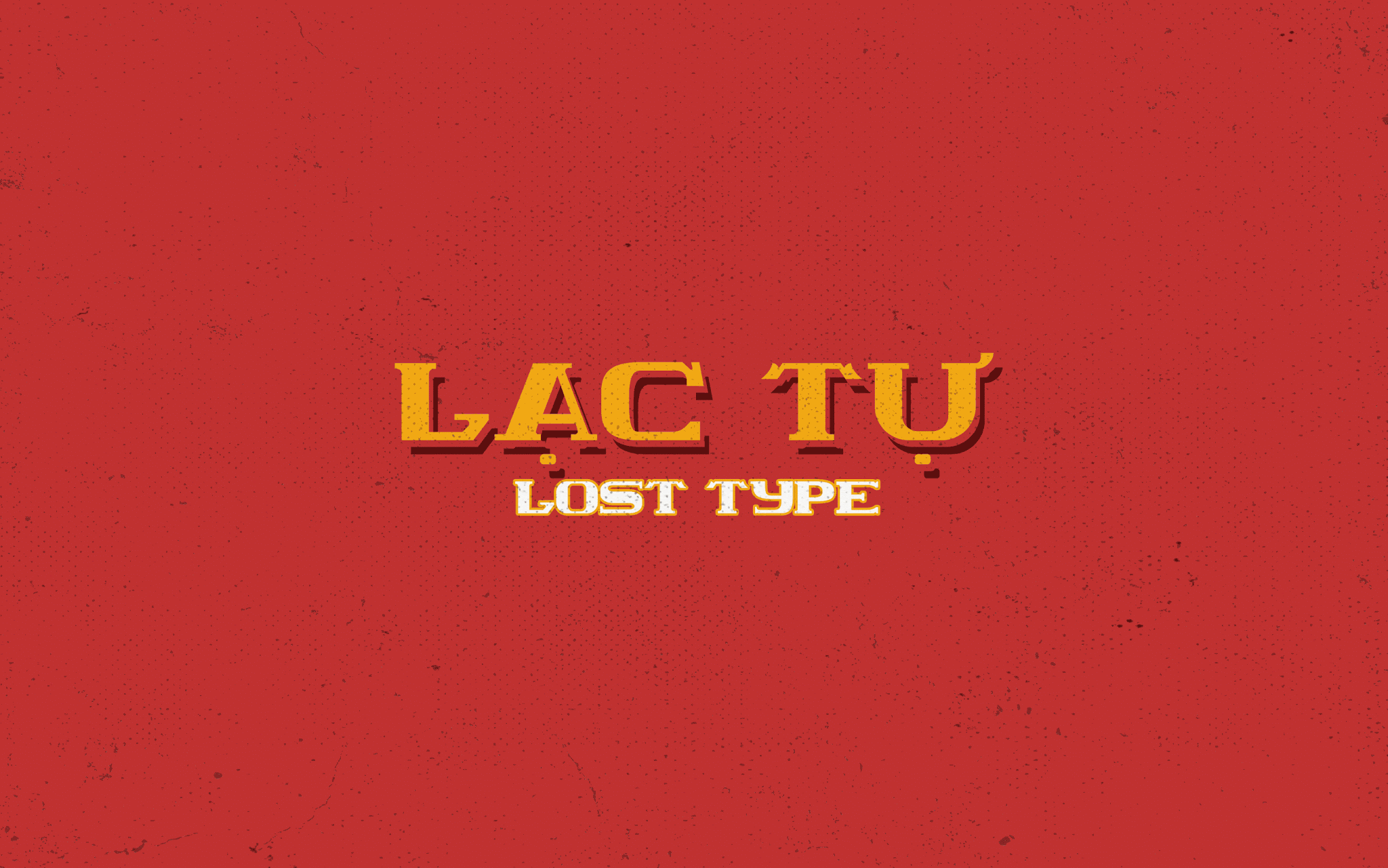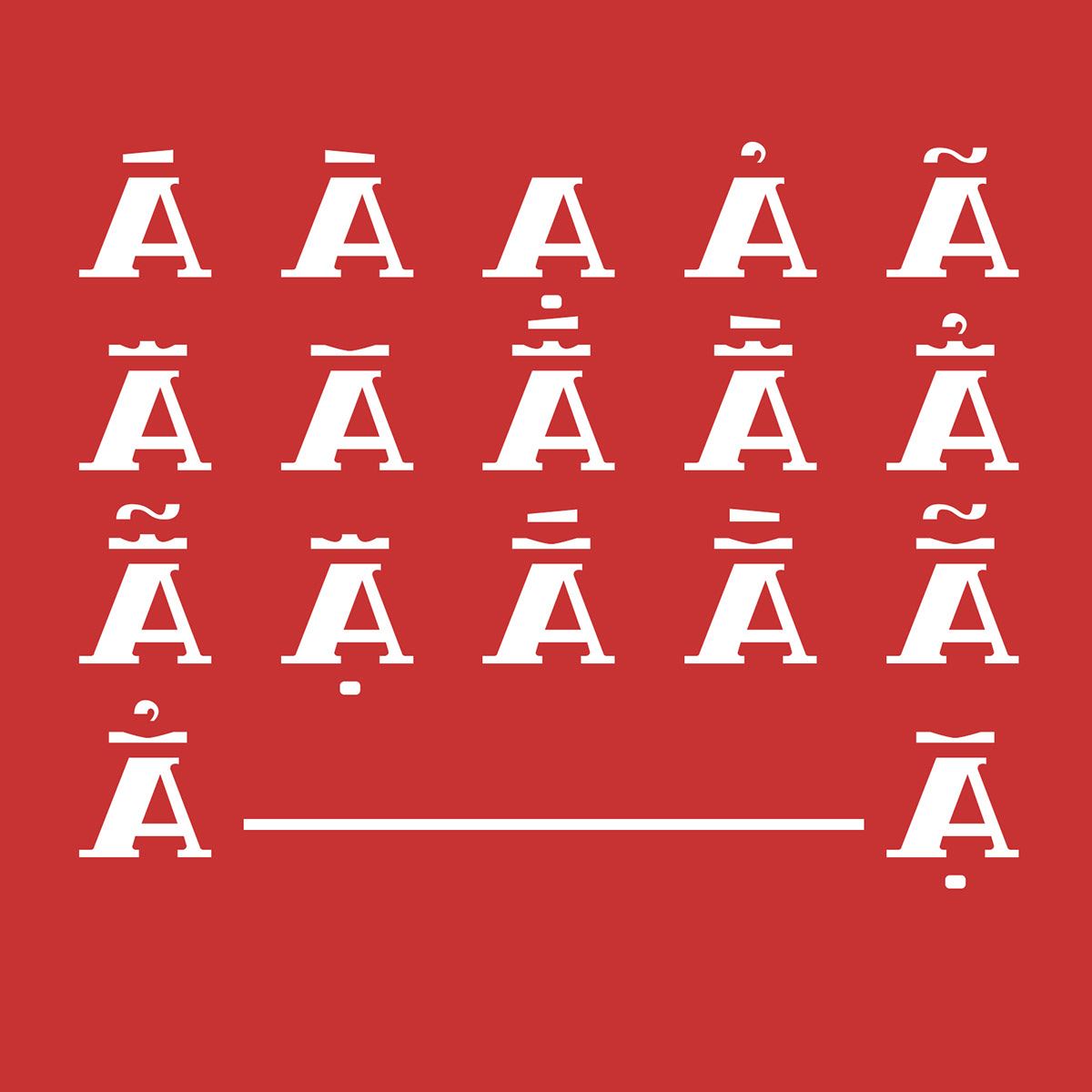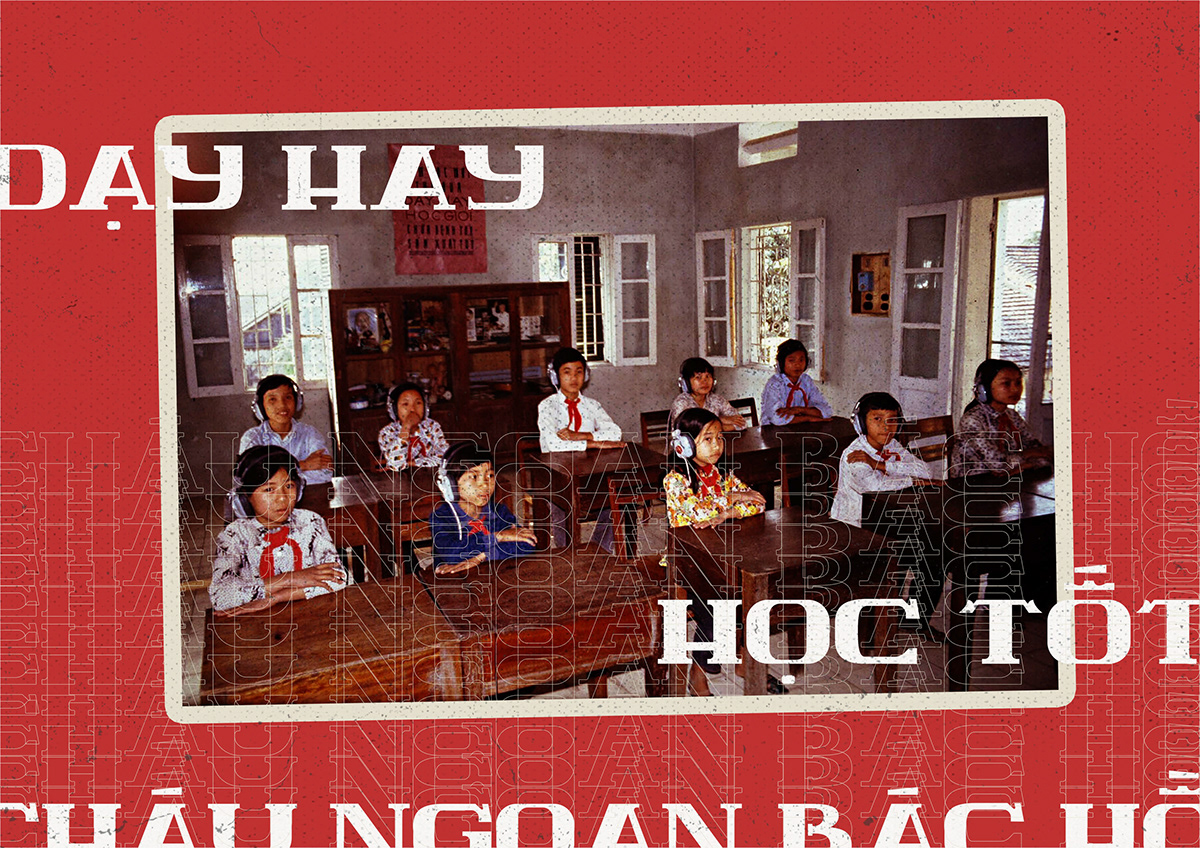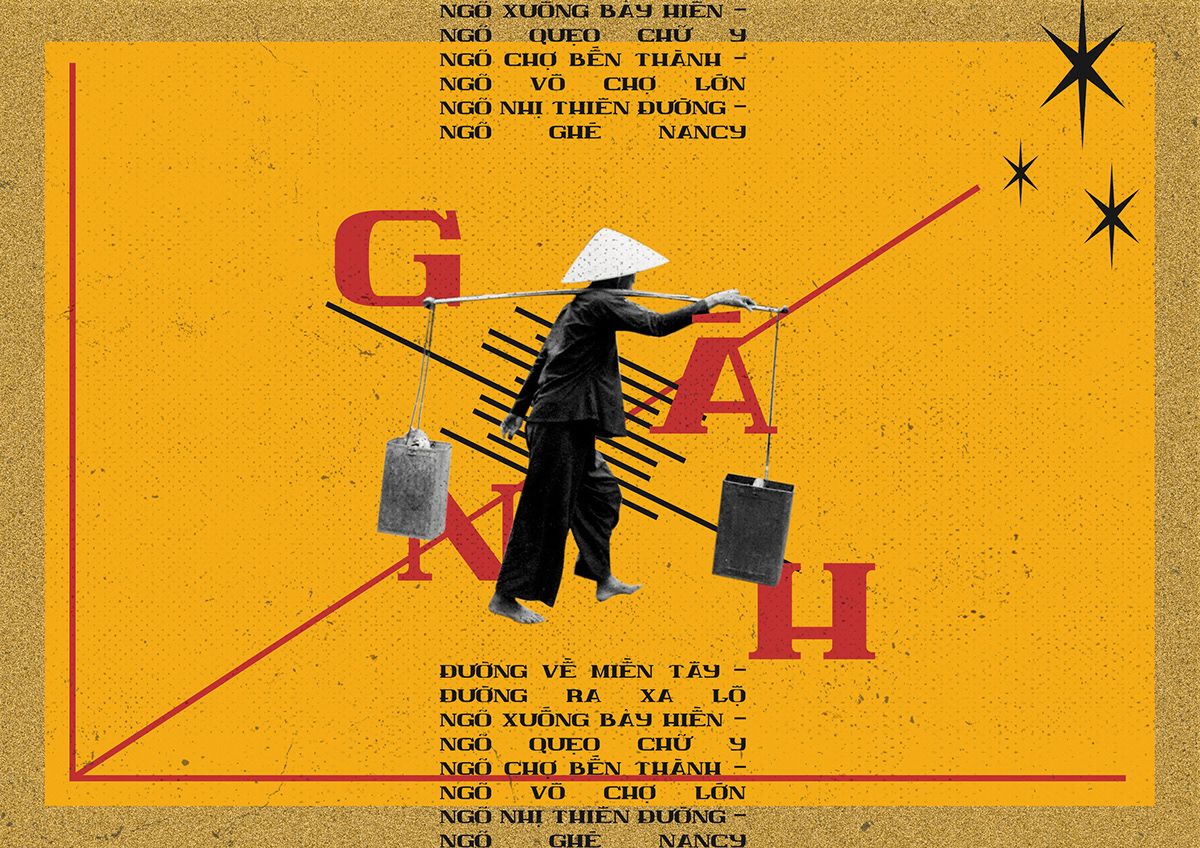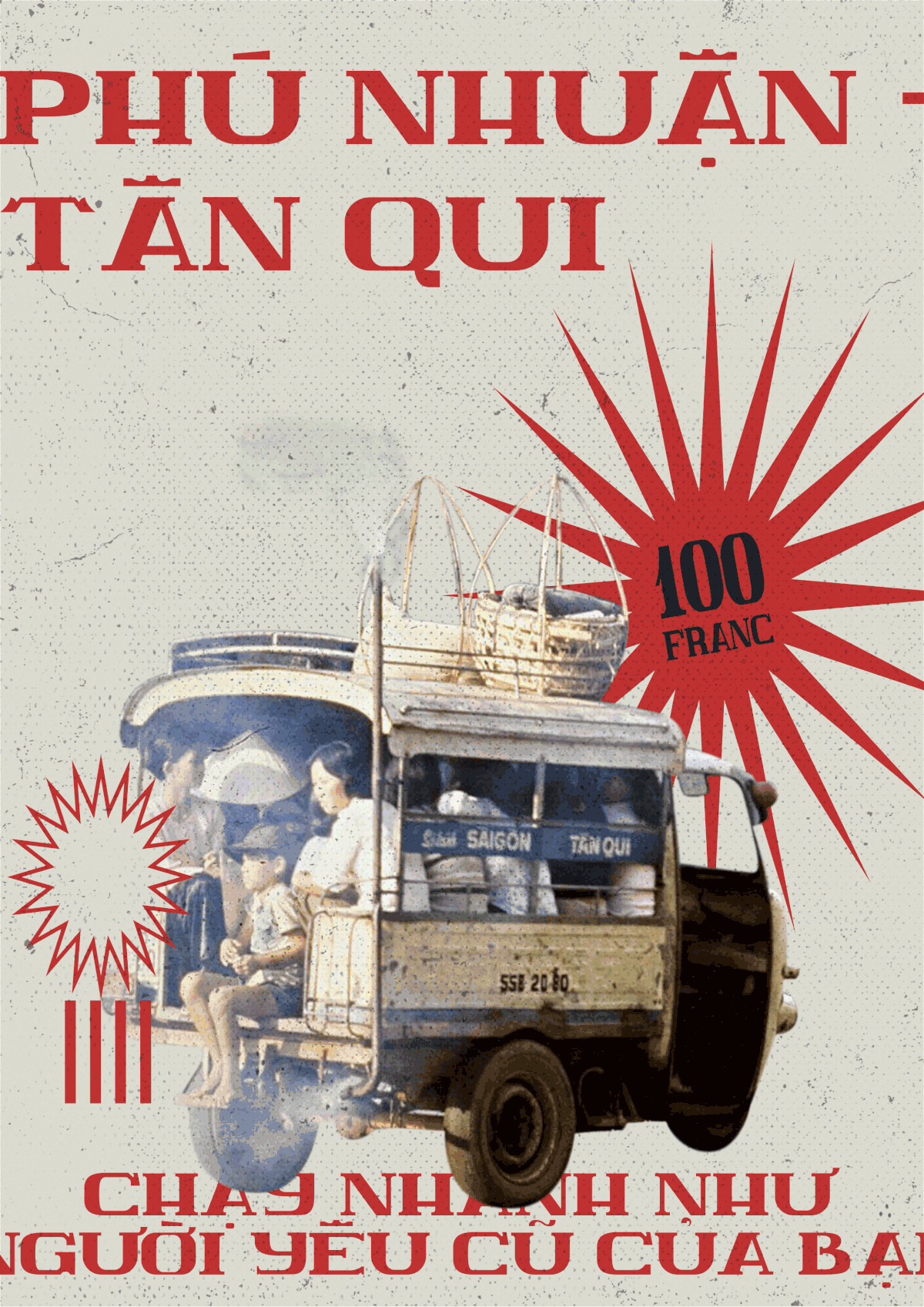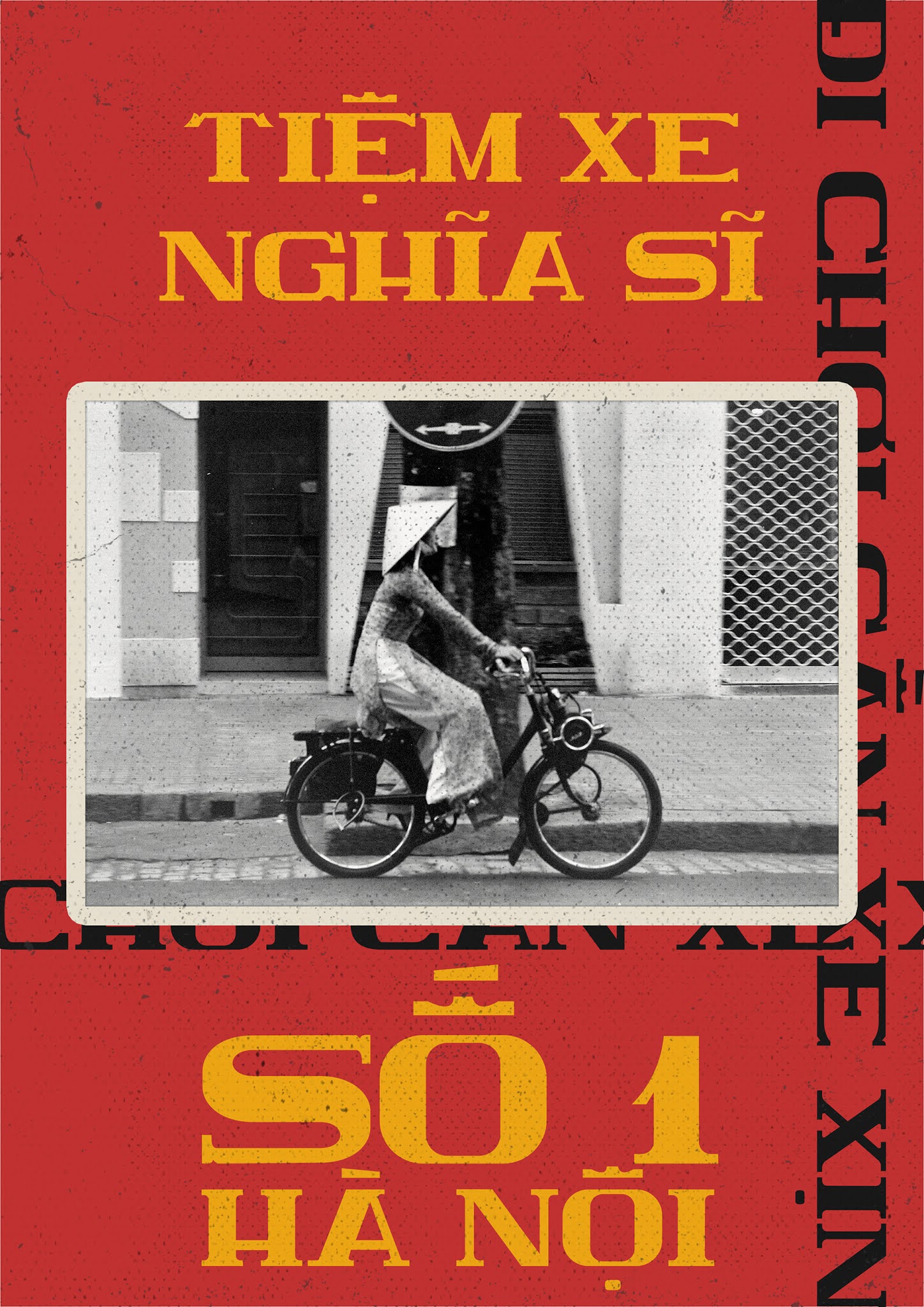
Tải font Lost Type (Lạc Tự) – Font dạng xưa cũ rất đẹp
Font Lost Type (Lạc Tự) đây là một dự án được thiết kế bởi bạn Mack Trinh. Kiểu font dạng xưa cũ rất đẹp và hiện đại.
Lost Type (Lost Vietnam) là kiểu chữ dựa trên kiểu chữ cổ điển ở Việt Nam trong khoảng những năm 1980 đến 1990. Kiểu chữ này được lấy cảm hứng từ các bảng quảng cáo thương mại tại các thành phố lớn của Việt Nam như Hà Nội và Thành phố Hồ Chí Minh. Bằng cách kết hợp các tính năng truyền thống với phong cách hiện đại, Lost Type vừa mang nét cổ điển vừa phù hợp hoàn hảo với các thiết kế đương đại. Chủ đề tổng thể là tạo một kiểu chữ thử nghiệm có màu đậm và nguyên bản.
Font Lost Type (Lạc Tự)
Font dạng xưa cũ Lost Type (Lạc Tự)
Font xưa cũ đẹp